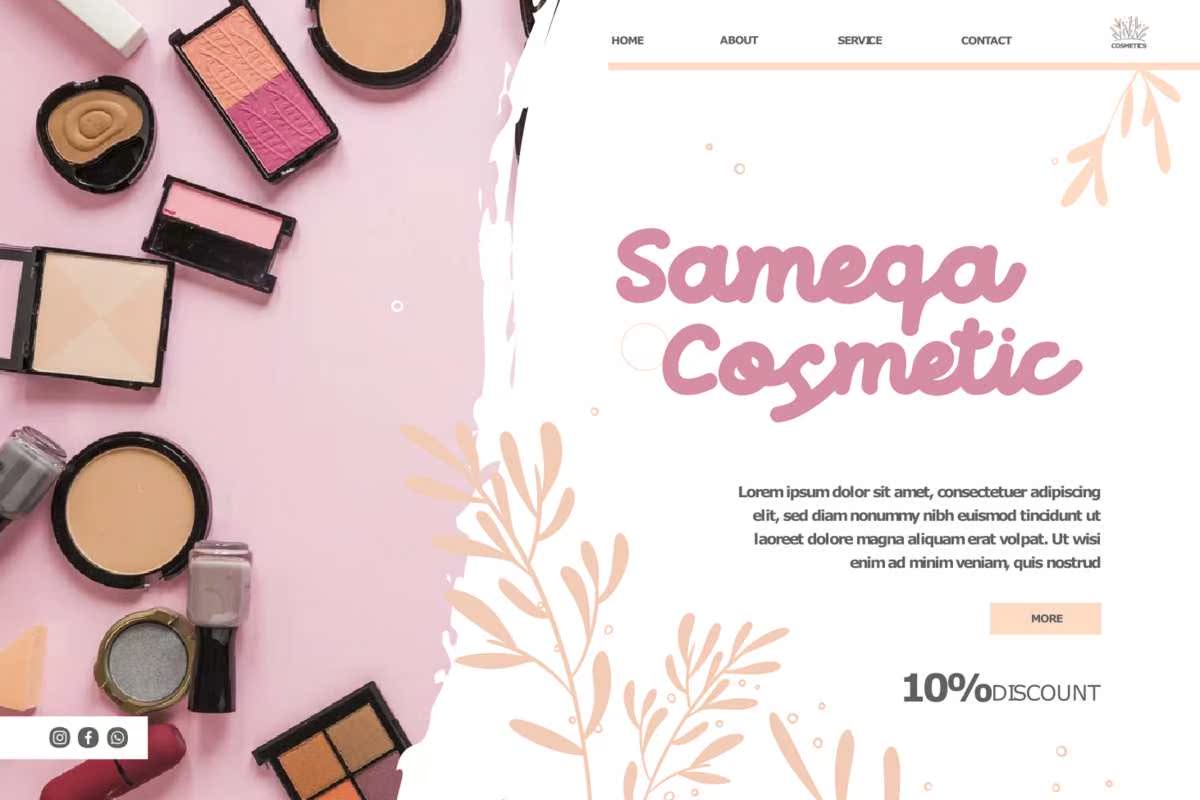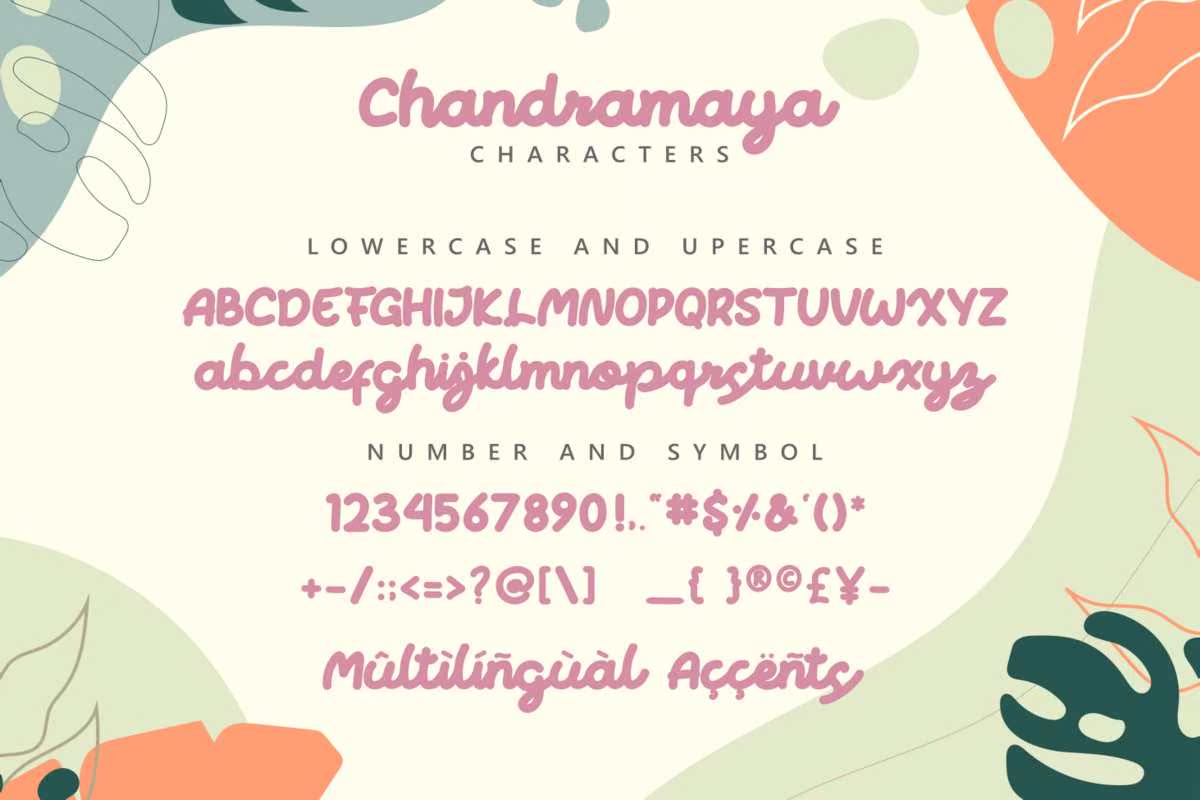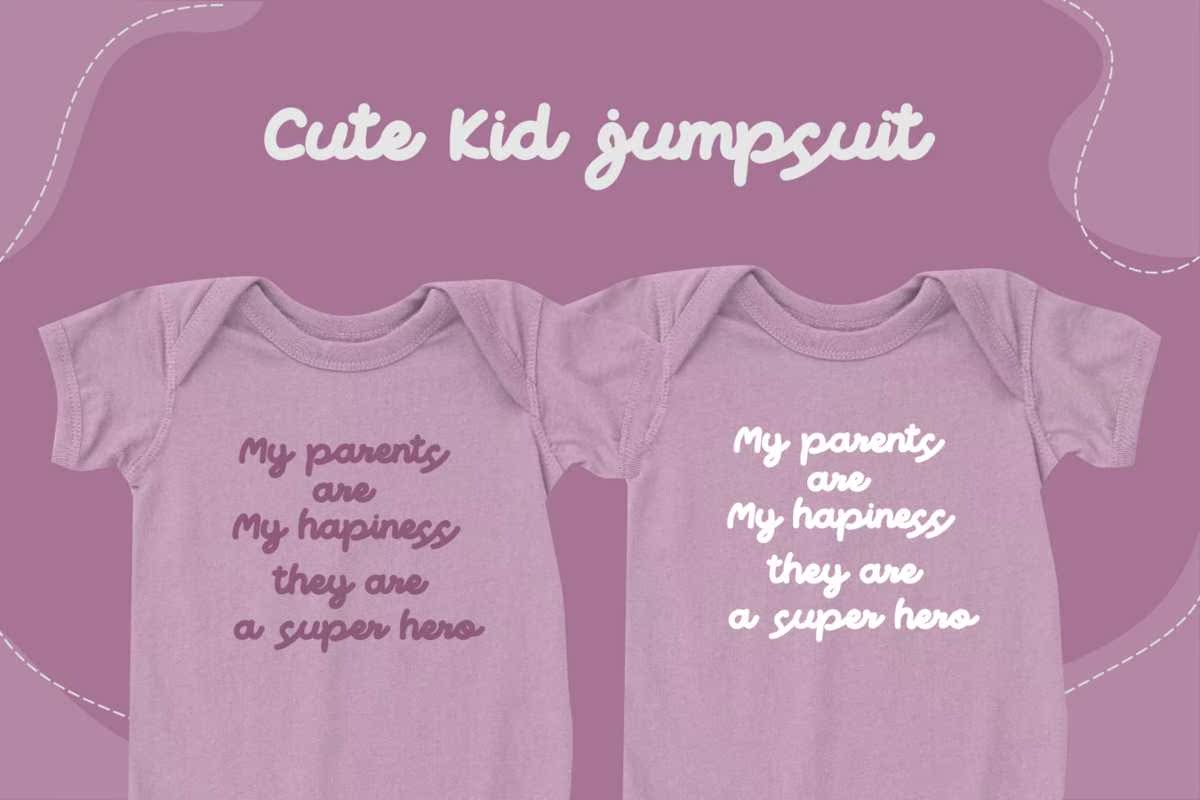
ChandramayaFont ScriptFont是一款现代写实的、美丽的、浪漫的剪贴画字体。它的特点是具有立体感、连字和涂鸦。这款字体美观大方,非常适合于书写项目,如增加灵感、美化艺术、吸引眼球的社交主题、引文、剪贴画和更多。ChandramayaFont ScriptFont是一款现代写实的字体,美丽和浪漫的彩绘字体。它的特点是立体感、连字和涂鸦。这种字体美丽而优雅,非常适合于书写项目,如增加灵感、美化艺术、吸引眼球的社交主题、引用、剪贴画等等。